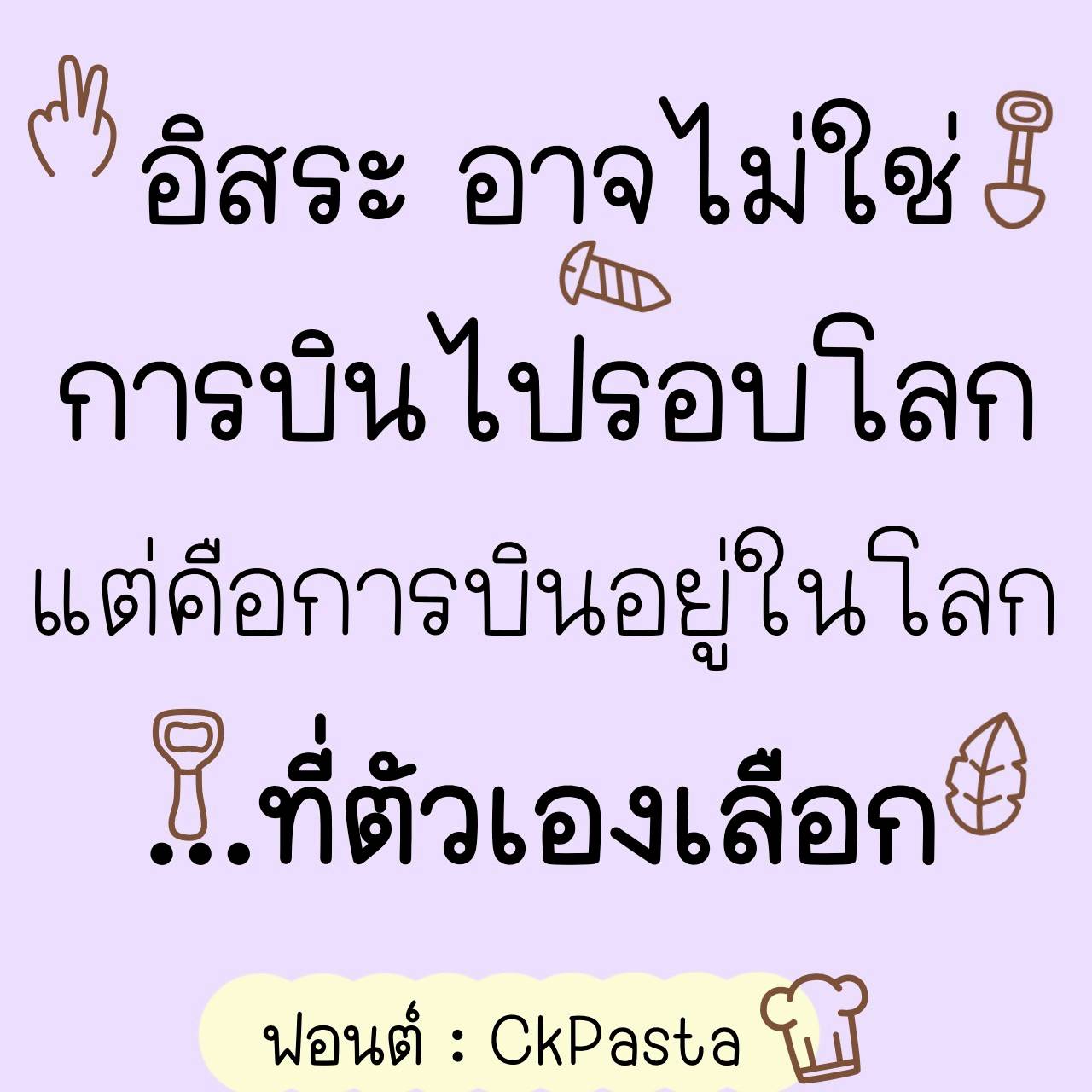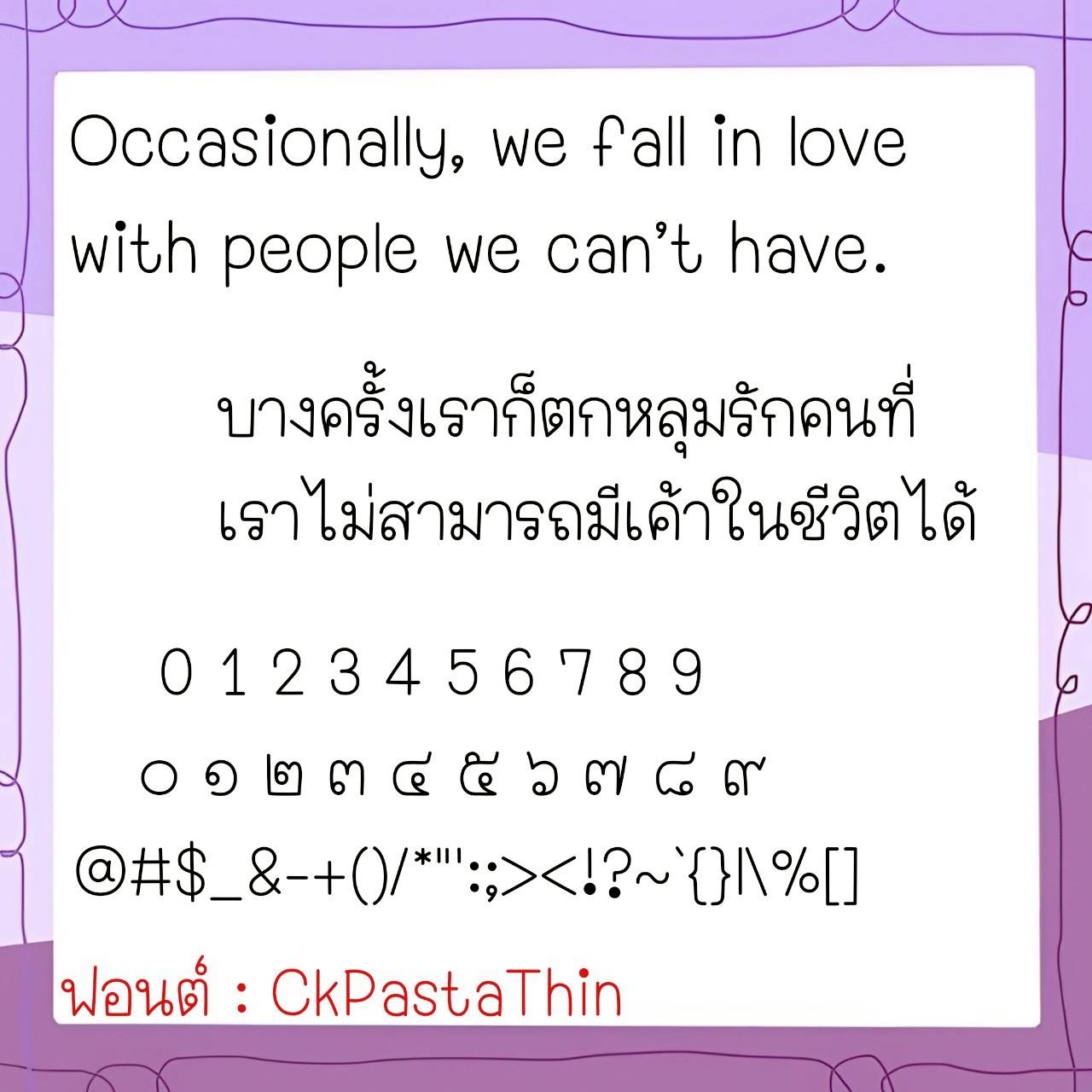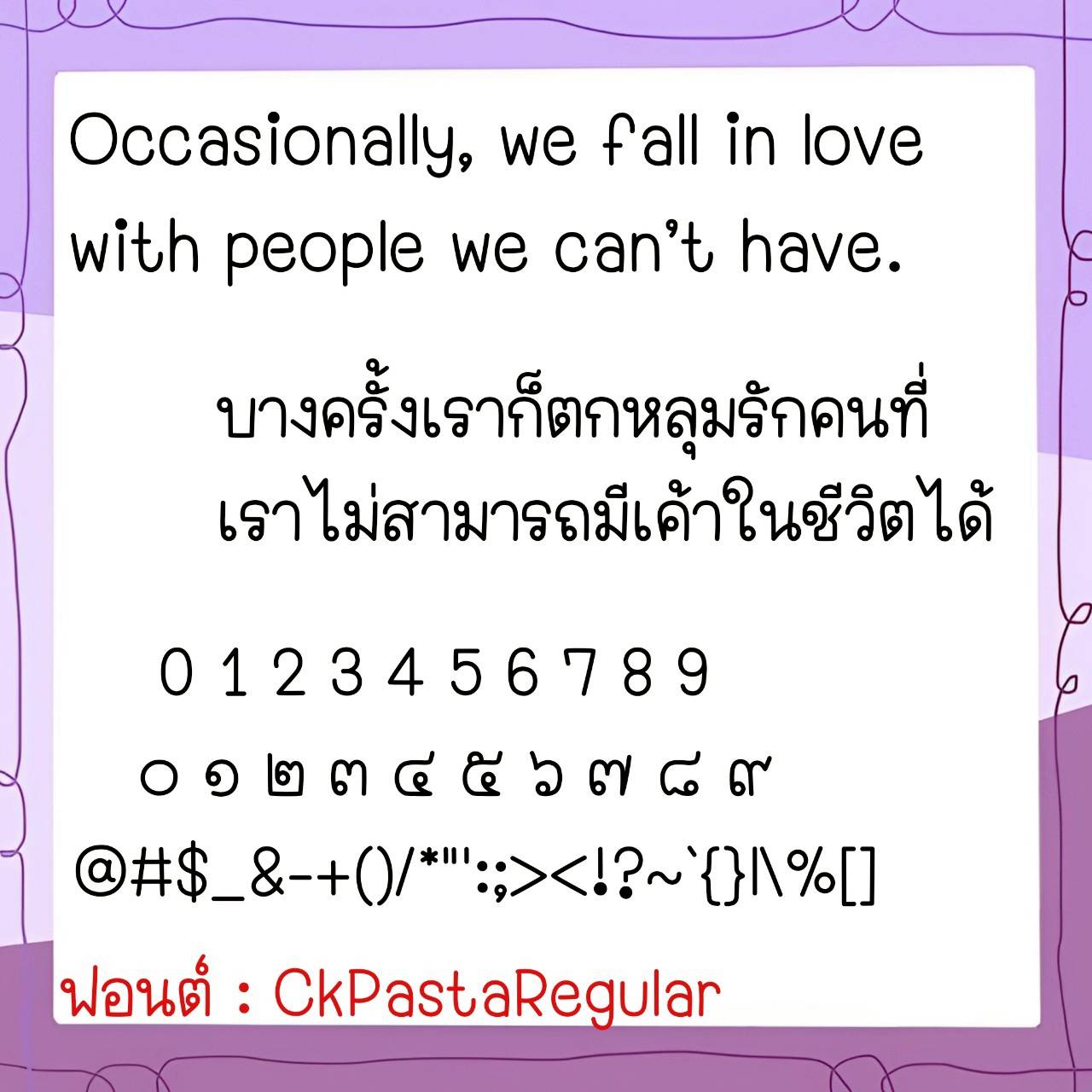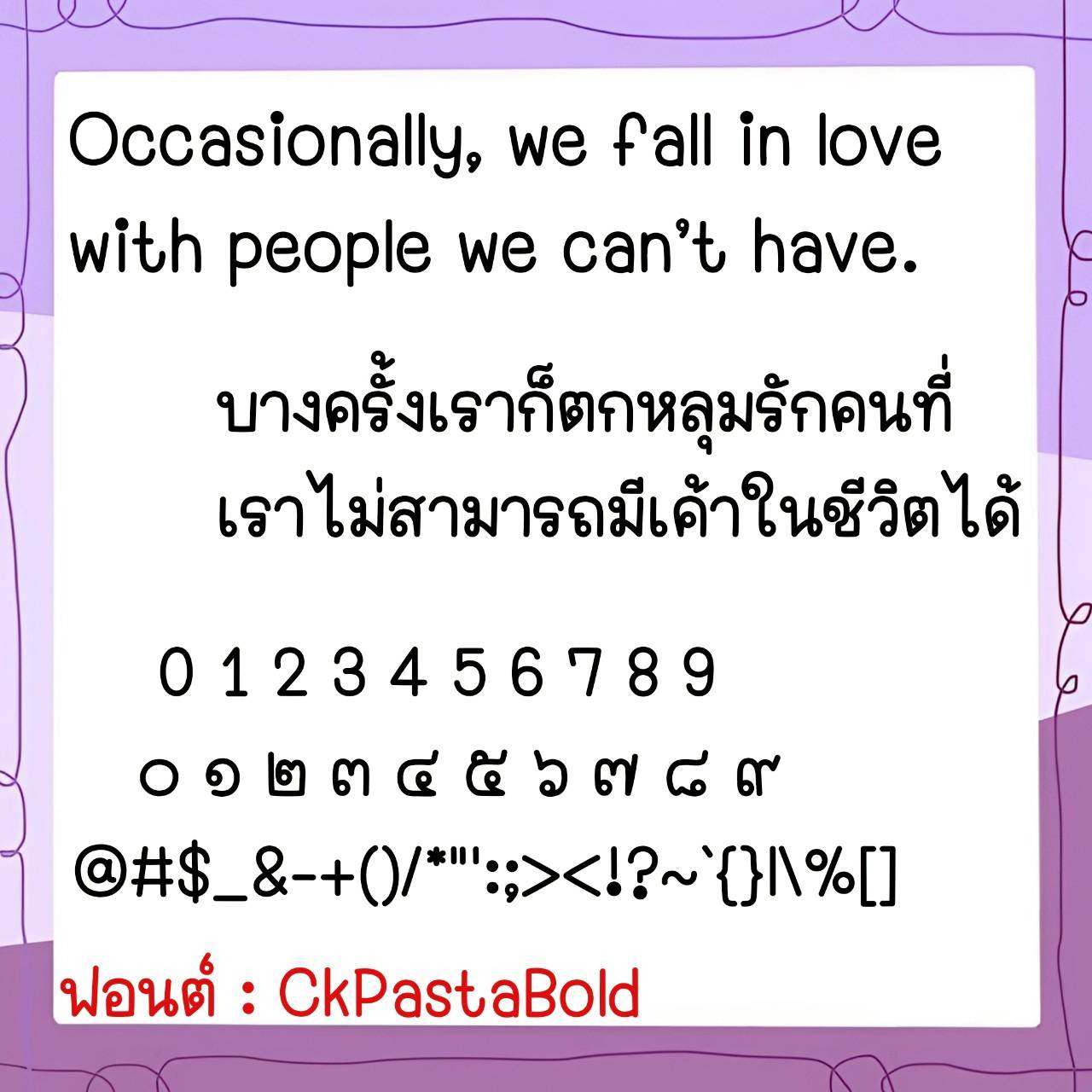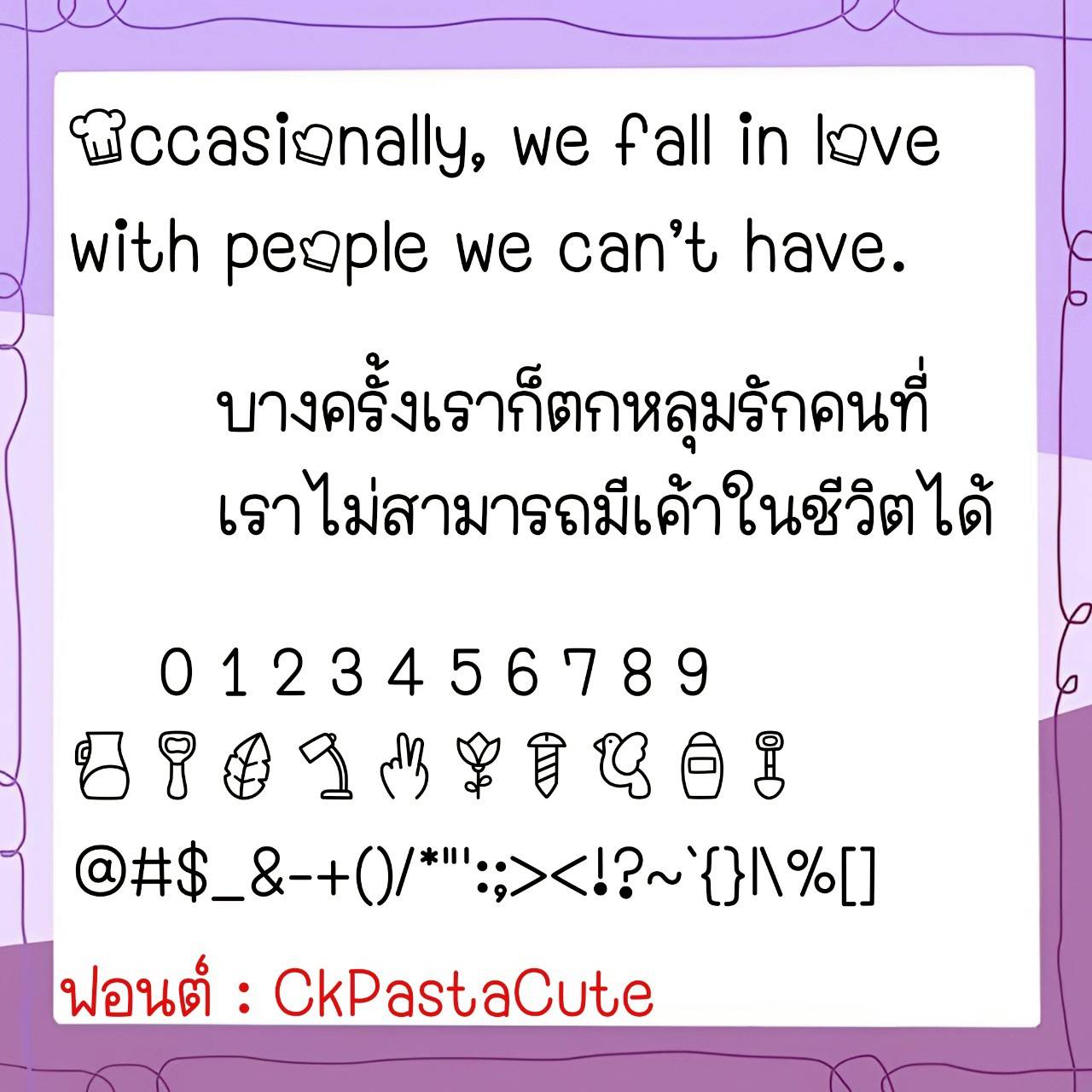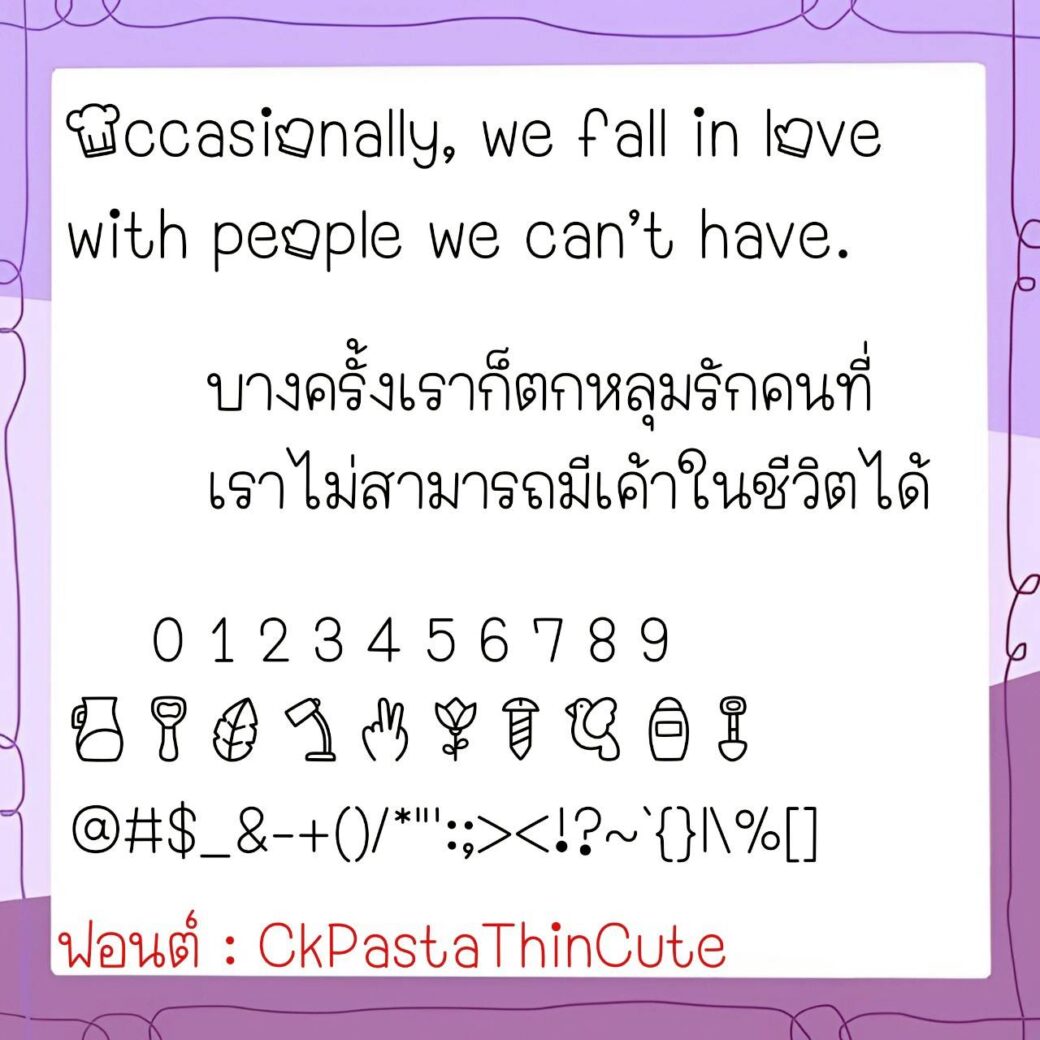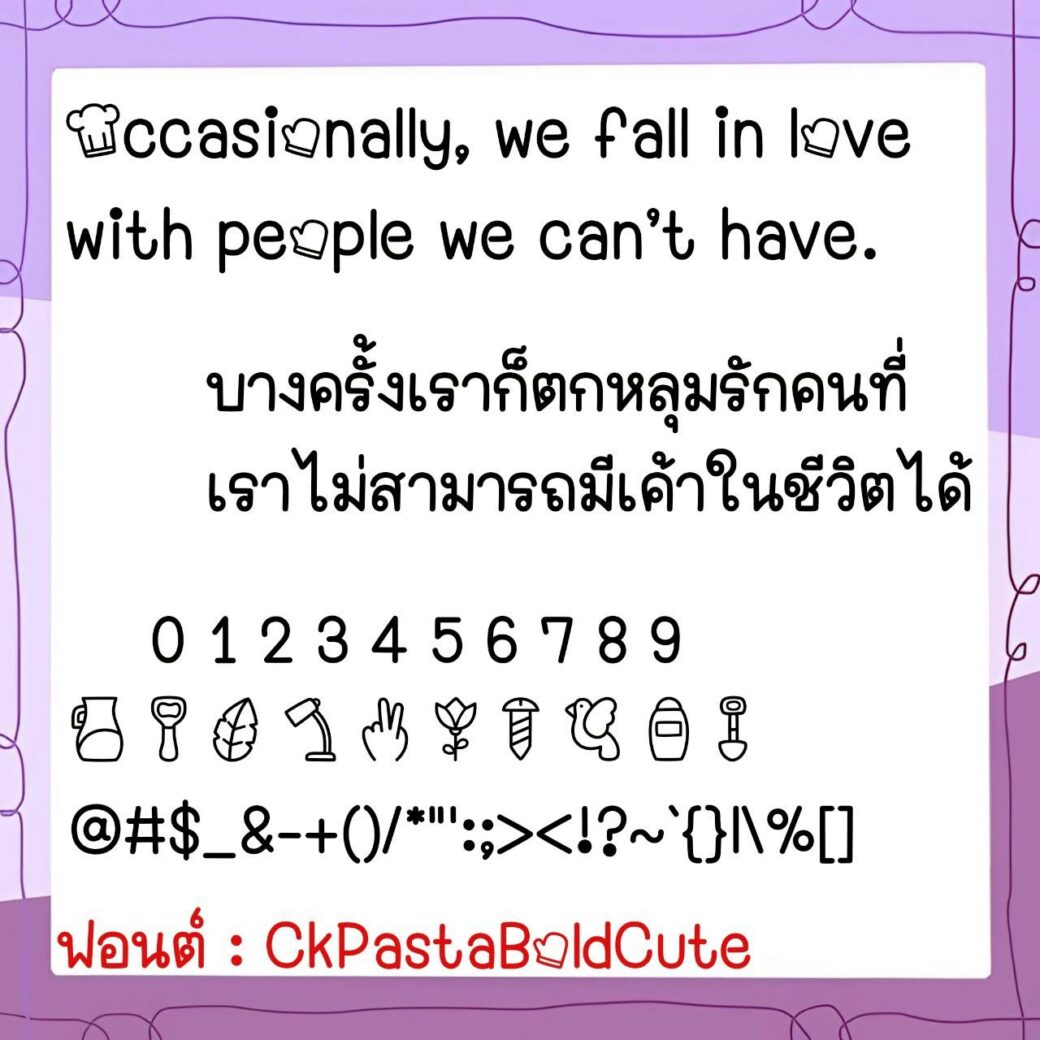
Font CkPasta
ชื่อสินค้า : Font CkPasta 💜
🔸 ฟอนต์ลายมือตัวอวบอ้วน มีความน่ารักแต่ยังดูเป็นระเบียบ เป็นฟอนต์ที่เห็นชัด อ่านง่ายสบายตามากๆ และยังมีไฟล์อิโมจิน่ารักๆ ที่ใช้แทนเลขไทยให้ด้วยค่ะ 🥰💙
🔹 The chubby handwriting font is cute but still looks neat. It is a font that is clear, easy to read, and very comfortable to the eyes. There is also a file of cute emojis that can be used instead of Thai numbers. 🥰💙